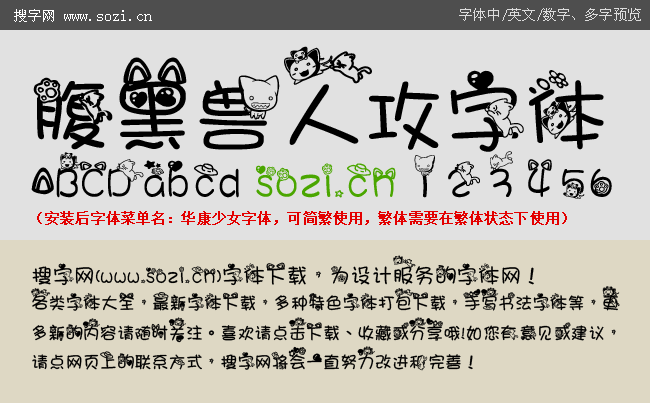
腹黑獸人攻字體
搜字網(wǎng)給大家提供一款很卡通的手機中文字體下載。修改者將它命名為腹黑獸人攻字體,這款手機字體是以華康少女體為原形,字體間配上了非常有趣的卡通圖案,華康少女字體電腦版是一款可愛俏皮的電腦字體。字型中充滿年青人蓬勃的氣息與自由奔放的性格,字體比較圓滑,特別適合喜歡手機字體個性一些的朋友在手機上安裝使用。